相信你的眼睛
字体设计是迭代地测试每个选择,共同合成一个完整的设计的进程。你将会一直测试字体,看你做出选择的合并结果是否能够:
- 对你来说可读
- 字体让你觉得好
- 字体对于你希望它能够完成的工作有帮助
在你测试设计的时候,你要相信自己的认知,设计实际的东西。许多字体设计都需要你设计的字体类似并且形式上重复。
人们很容易认为如果你测量字形的组成部分和间距,那么你将得到可靠的结果。虽然很有用,但是这个方法有实际的限制。如果有什么看起来错了,那么你应该期望做出调整。更进一步来说,你应该确信正确的做法是作出修改直到它“看起来正确”。
这正确的原因是由一些所有读者都会有的自然的视觉错觉。这些错觉必须在你修改字母形状的时候计算在内,直到他们看起来正确。
通过这些视频(外部链接)你可以大致的了解一般都是通过修改或者注意哪里来修正这些视觉错觉。
错觉的例子
一些错觉涉及对线条的粗细的感知,一些涉及线条的长度,另一些设计形状的感知。
水平与竖直的粗细程度
左边的例子展示了一个条形粗细相同的“H”。这看起来是不对的。你能感受到吗?右边的另一个水平的条形做的更细,这样看起来粗细相等。
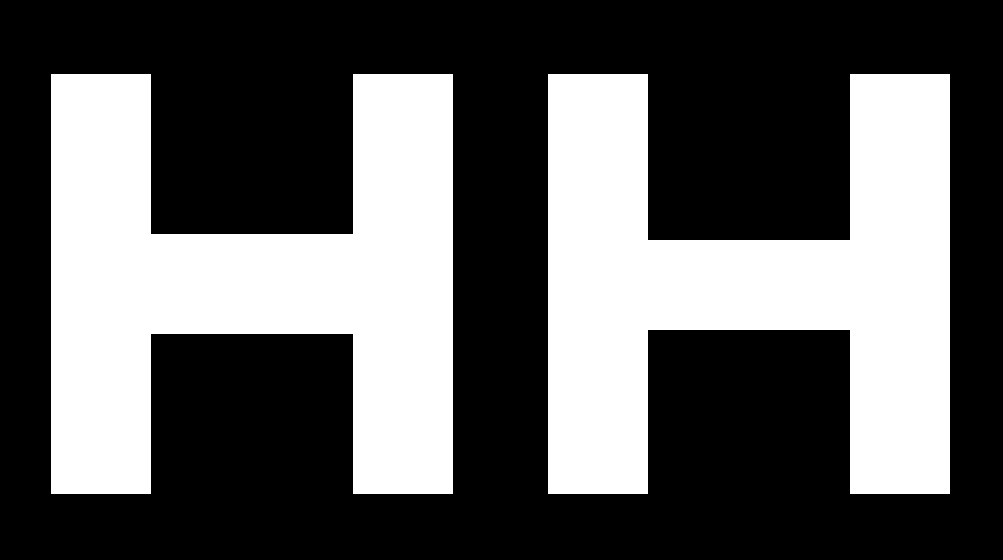
需要按照视觉做出调整的字形有很多,包括 A、E、F、L、H、f、t 和 z。
斜向粗细
类似地,如果一些条形宽度相等,其中一个放在斜线上,那么斜向的条形看起来比竖直的条形粗并且比水平的条形细。如果你想让它看起来正确,那么你不得不像水平的例子一样将其调细一点,但是只是细一点点。
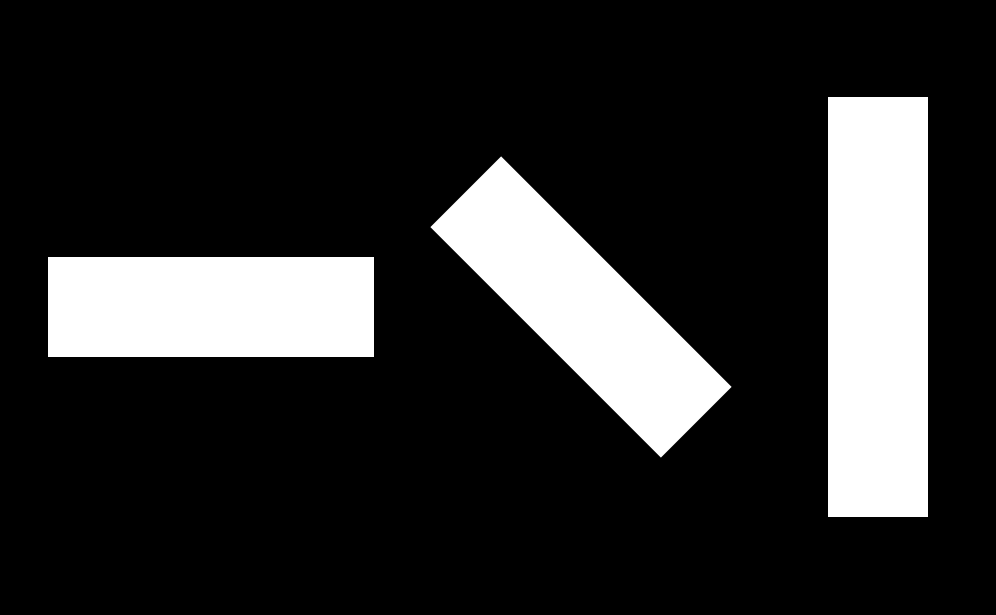
令人产生错觉的相关字形十分多,包括 k、K、N、Q、R, v、V、w、W、x、X、y、Y、7、2、&、ł、Ł、ø、Ø、√、∕、‹、›、 «、»、½、⅓、¼、≤、≥ 和 ×。
宽度和对斜向角度的感知
更长的图形需要比短的图形倾斜更少,这样表面上看起来他们倾斜度相同。
下面的图中的斜线倾斜角度相同。长的那个看起来角度不同。
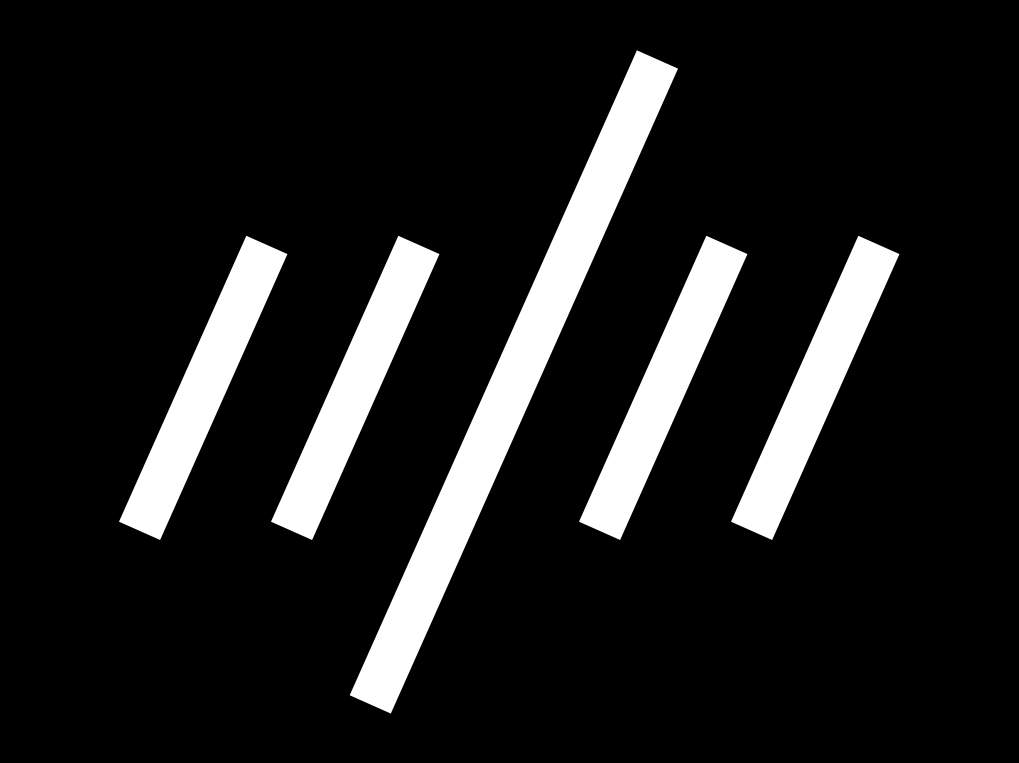
在下图中,长的线条的倾斜程度被调整过:
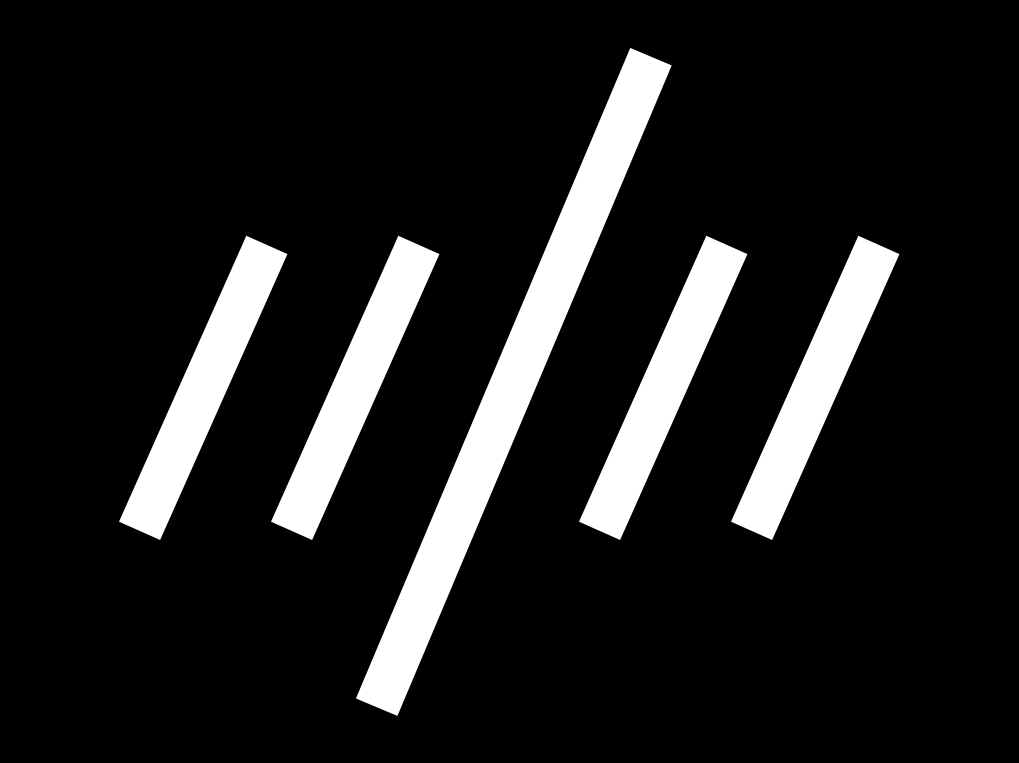
现在我们来看真实的斜体,在字形上应用了这些修正:
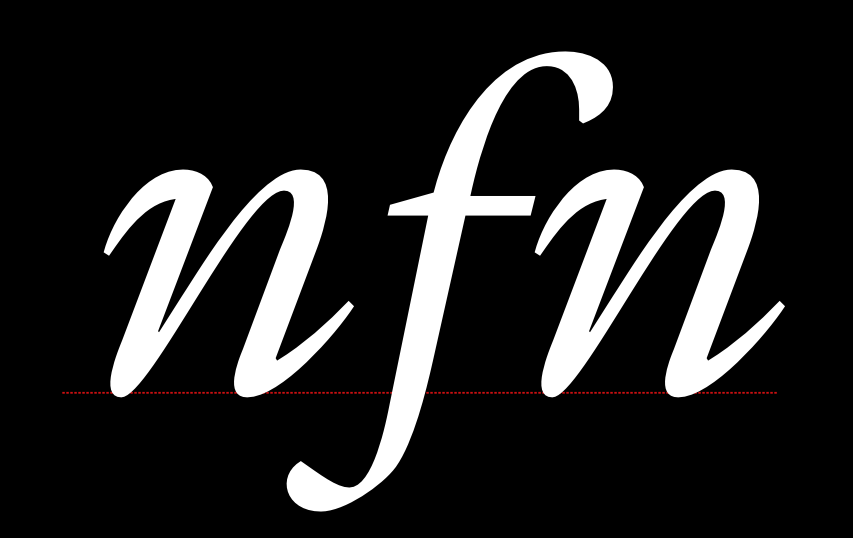
交叉斜线
当一个条形穿过另一个斜线或者直线时,需要调整它以便看起来不像是没有对齐。
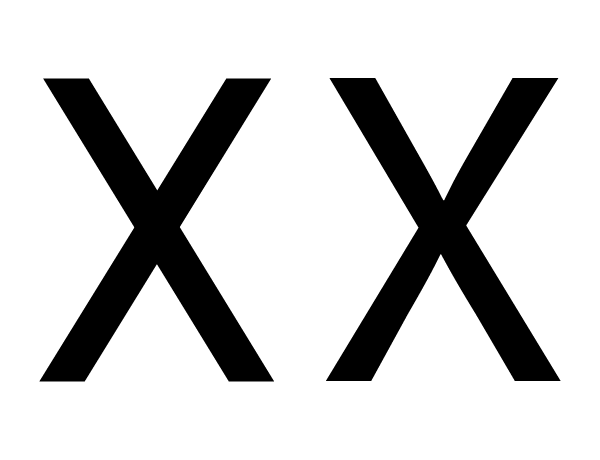
上面的例子中,左边的 X 由两个未调整的条形互相交叉。右边的例子被调整过,这样看起来是对齐的。
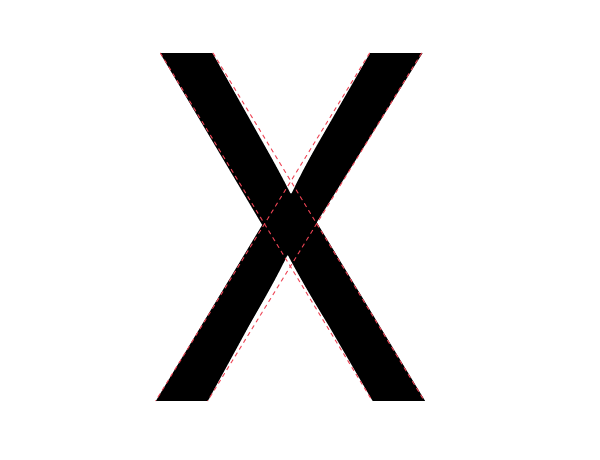
在这个 X 中通过虚线你可以看到看起来显得对齐的 X 实际上有偏移。
涉及到这个错觉的字形包括 x、X、k、K、×、#和冰岛语字母“eth”(ð)。
高度感知
一个字形的形状将会对它看起来和其他字形高度一致时的高度产生作用。圆的字形需要超过平的字形的高度一点点。包含尖的形状的字形需要超过更多。形状越尖锐,它为了看起来正确需要超过的就更多。
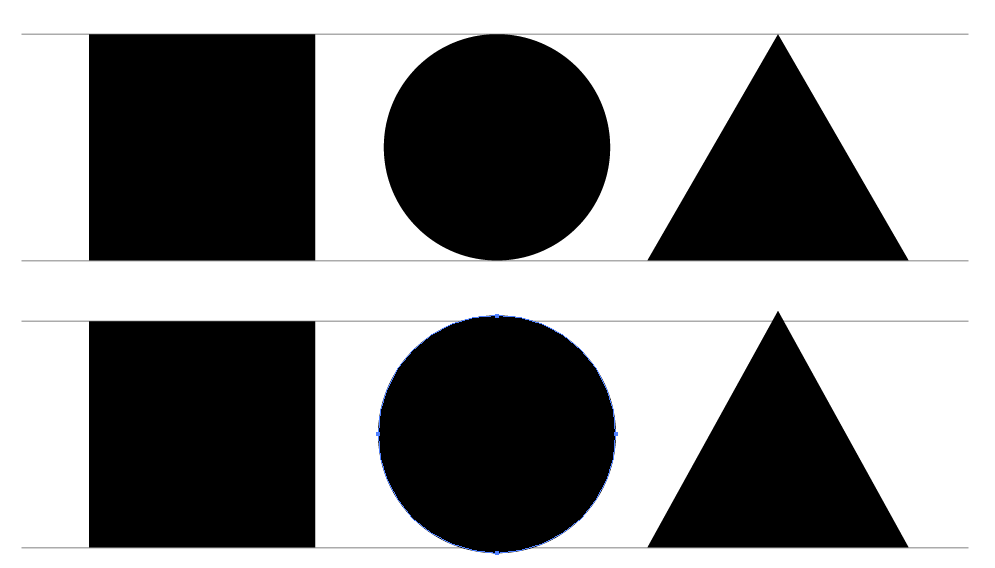
在上图中,上面的三个图形没有经过调整,也就是他们有完全相同的高度。下面的三个图形经过调整,看起来有更加接近的高度。
这一错觉涉及到包含圆的或尖的部分的人和字形,包括 O、Q、C、S、A、V、W 等。
你完全有资格来纠正这些错觉
由于你既能看到错觉,也能看到修正错觉的效果,所以你能够自行作出这些修正。你仅仅需要相信你的印象。
测试目的的适当性
就像你能够看到光学错觉并纠正他们一样,你也有能力去分辨一个字体是否胜任你心目中特定的用途。在这一点上你也同样需要相信你的判断。
值得一提的事没有字体能够在离开其使用方式和目的的情况下被评估。这也是测试需要从设计进程最开始一直到你觉得项目完成的原因。
这些测试会是什么样子呢?开始的测试比较简单,你只需测试第一个设计的选择。随着你的设计变得更加完整,你的测试需要跟上进度并且能够评估你所做的最新的决定相对成功还是失败—或者更好的情况是能够比较你所考虑的 2 个(或者 3 个或者更多…)选项。
有时你将发现你不得不折返修改你之前认为已经足够好的设计选择。这是常态。制作一个字体需要平衡很多因素,惊奇经常会发生。设计的字体越多,你做任意选择的经验也就越多。
当接近进程的尾声的时候,如果字体采用简单的方式来使用,那么测试也应该保持简单。但是如果一个字体将会有多种使用方式,或者在大范围的打印或屏幕环境下使用,那么测试应该覆盖这些情况的所有范围,包括打印字体的各种样例。
如果你对你打算的最终用途有明确定义的想法,那么设计时间将得到节省。但是这并不总是可行的,你的想法可能发展。关键的东西是考虑并定义尽你所能完整的用例,然后确保在设计字体时你的测试跟上你问自己的问题。